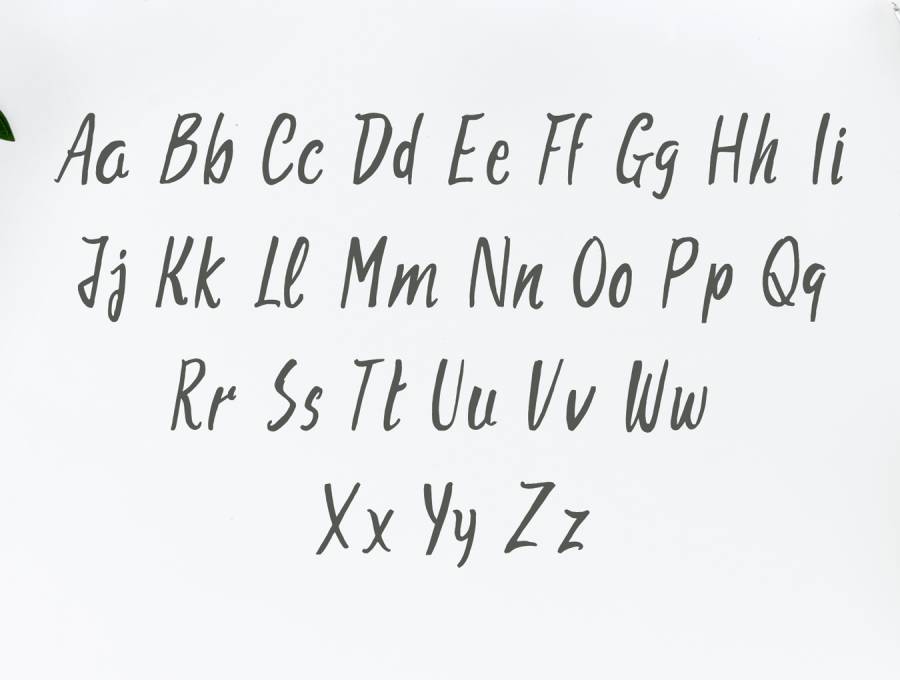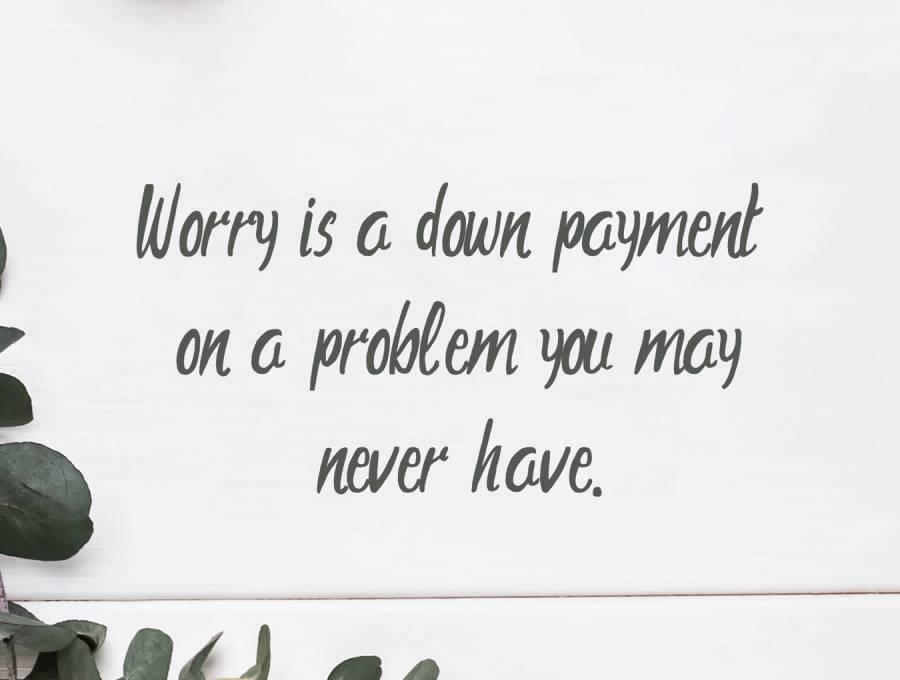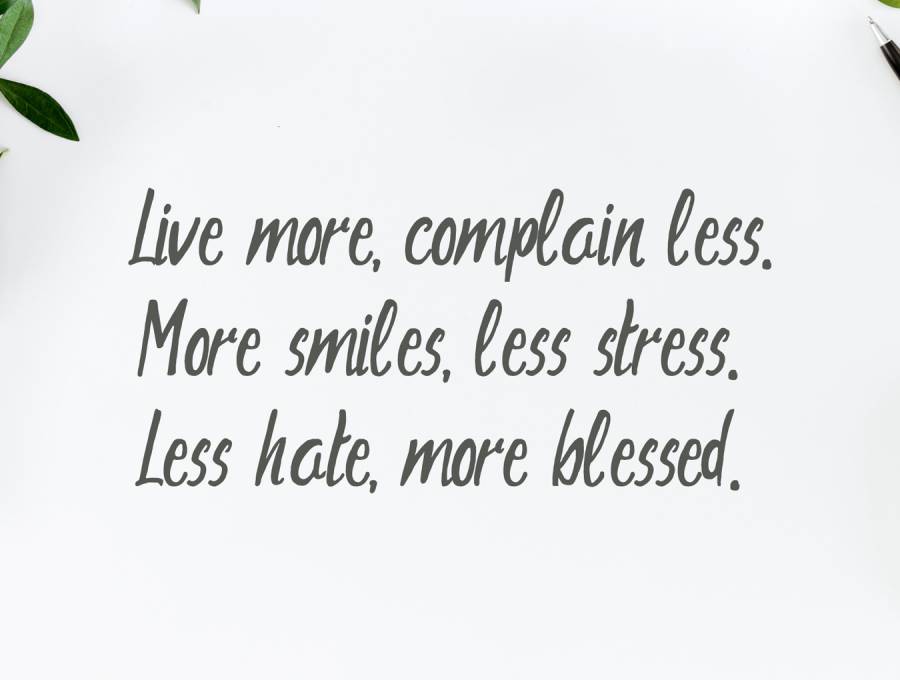
现代直手写OTF,TTF,WOFF&WOFF2刷字体。,Aharon刷字体
Modern Straight Handwritten OTF, TTF, WOFF & WOFF2 Brush Font., Aharon Brush Font
Aharon是一款现代笔直手写笔刷字体。它是一种独特的手写字体,非常适合用于所有与设计相关的项目,如打印,徽标,签名,报价,徽章,标签,标题,横幅,打印机,印刷品,T恤,杂志,包装设计,博客,网站,设计,促销,产品,模板等